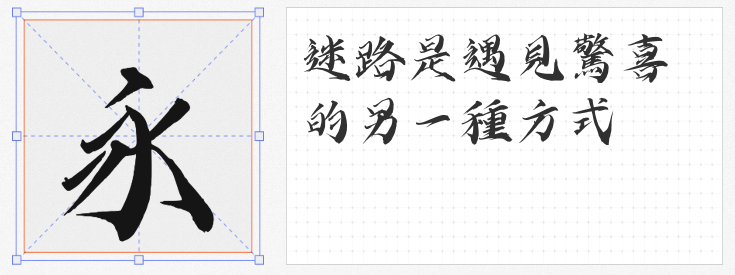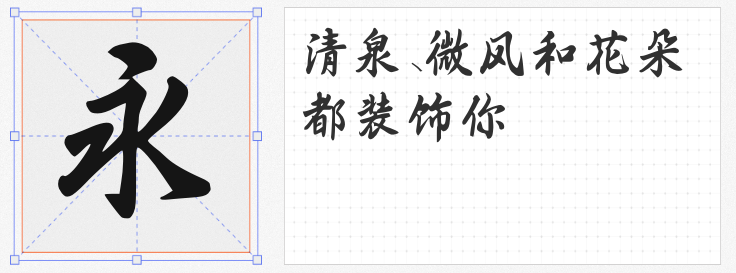
在国风设计复兴的浪潮中,书法字体作为文化基因的载体,既是视觉表达的灵魂,亦是意境营造的根基。以下四款字库字体,以传统书法为骨、数字技术为翼,在规范性与艺术性间寻得精妙平衡,为设计注入浑厚的历史底蕴与鲜活的当代生命力。
1. 阿里妈妈东方大楷
源于颜真卿《多宝塔碑》的算法解构与人工精修,这款字体以丰腴饱满的笔画重塑经典。机器学习精准捕捉了颜体“蚕头燕尾”的笔势特征,通过骨架规范与笔画收放,将书法中的落笔力度、转锋韵律转化为可复用的数字语言。其浑厚圆融的视觉效果,既保留了手写书法的温度,又以标准化结构适配多元场景,堪称“数字时代的颜筋柳骨”。
2. 阿里妈妈刀隶体
以《爨宝子碑》为灵感源泉,这款字体以刀刻斧凿的棱角颠覆传统隶书的温润。三角点折的锐利转折与横画“雁尾”的方硬收笔,强化了外露锋芒的视觉冲击;非对称结构与大胆布白,在失衡中暗合力学平衡,形成“险中求正”的动态张力。其稚拙倔强的气质,为设计注入一股打破常规的野性力量。
3. 字屿云游手书
这款字体以行草为基底,通过局部形变与笔势外拓构建整体气势。露锋用笔贯穿始终,结体紧致而不失灵动,曲线的大量运用赋予字形如流云萦绕的飘逸感,而转折处的铿锵力道则暗藏剑锋般的锐劲。阴柔与阳刚、含蓄与强劲的矛盾统一,使其成为表达东方哲学“刚柔并济”的理想载体。
4. 熊子杰行书
由专业书法家熊子杰手创,这款行书字体以遒劲笔力为骨,圆润转折为肉,在刚柔相济中展现书家个性。数字技术保留了手写时的提按顿挫,使每个字符都蕴含独特的节奏感。其规范而不失生动的笔画形态,既适合承载严肃的文化叙事,亦能诠释轻盈的现代美学。
四款字体,或承千年碑帖之魂,或抒当代书家之志,以数字笔墨重构国风设计的视觉语言,为传统文化注入可感知、可传播的现代生命力。